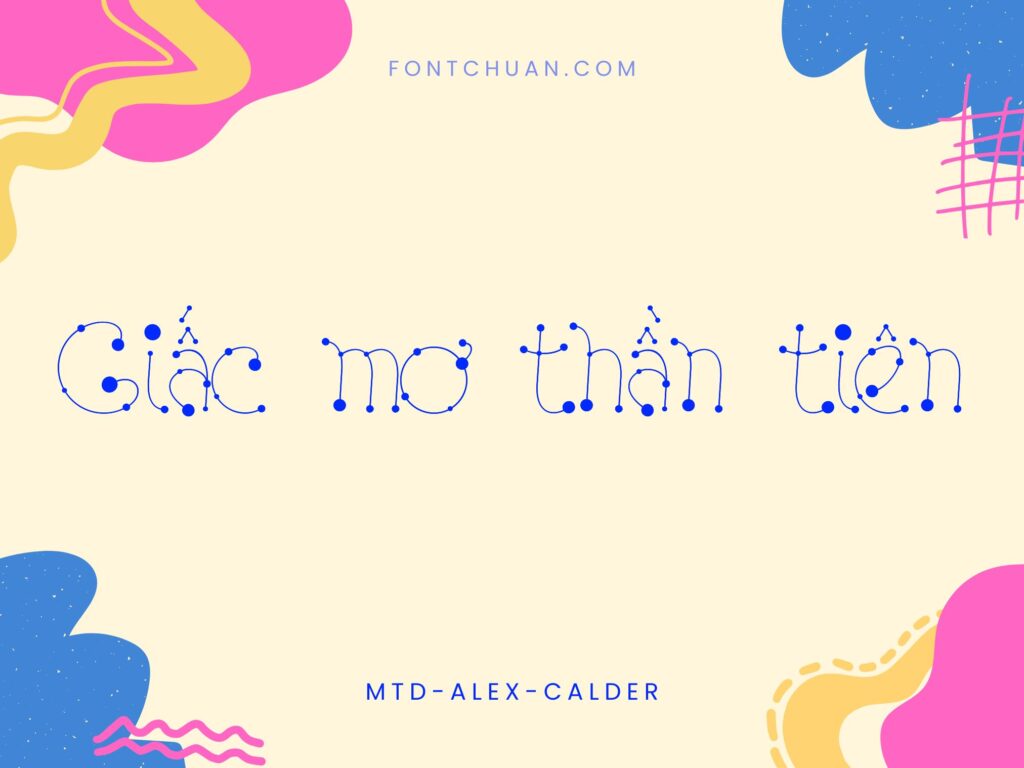
Font Alex Calder là một kiểu chữ trang trí độc đáo, được thiết kế bởi Etewut Foundry. Lấy cảm hứng từ nghệ sĩ điêu khắc người Mỹ Alexander Calder, font này mang đến sự kết hợp giữa nghệ thuật và sự sáng tạo, phù hợp cho các dự án thiết kế đòi hỏi tính thẩm mỹ cao.
Phiên bản Alex Calder đã được Việt hóa bởi Mộc Hạ, hỗ trợ đầy đủ tiếng Việt cùng hơn 15 ngôn ngữ khác như Anh, Pháp, Tây Ban Nha, Đức, Ý và Bồ Đào Nha, mở rộng khả năng ứng dụng trong thiết kế đa ngôn ngữ. Font này đã được thành viên Font Chuẩn sưu tầm và chia sẻ, đáp ứng nhu cầu của cộng đồng thiết kế. Với thiết kế bao gồm các ký tự trang trí tinh tế và phong cách nghệ thuật độc đáo, Alex Calder phù hợp cho các ứng dụng như thiết kế logo, tiêu đề, bao bì sản phẩm và các ấn phẩm quảng cáo. Các ngành nghề như quảng cáo, giáo dục, công nghệ và ẩm thực có thể tận dụng font này để tạo ra thiết kế ấn tượng và thu hút.